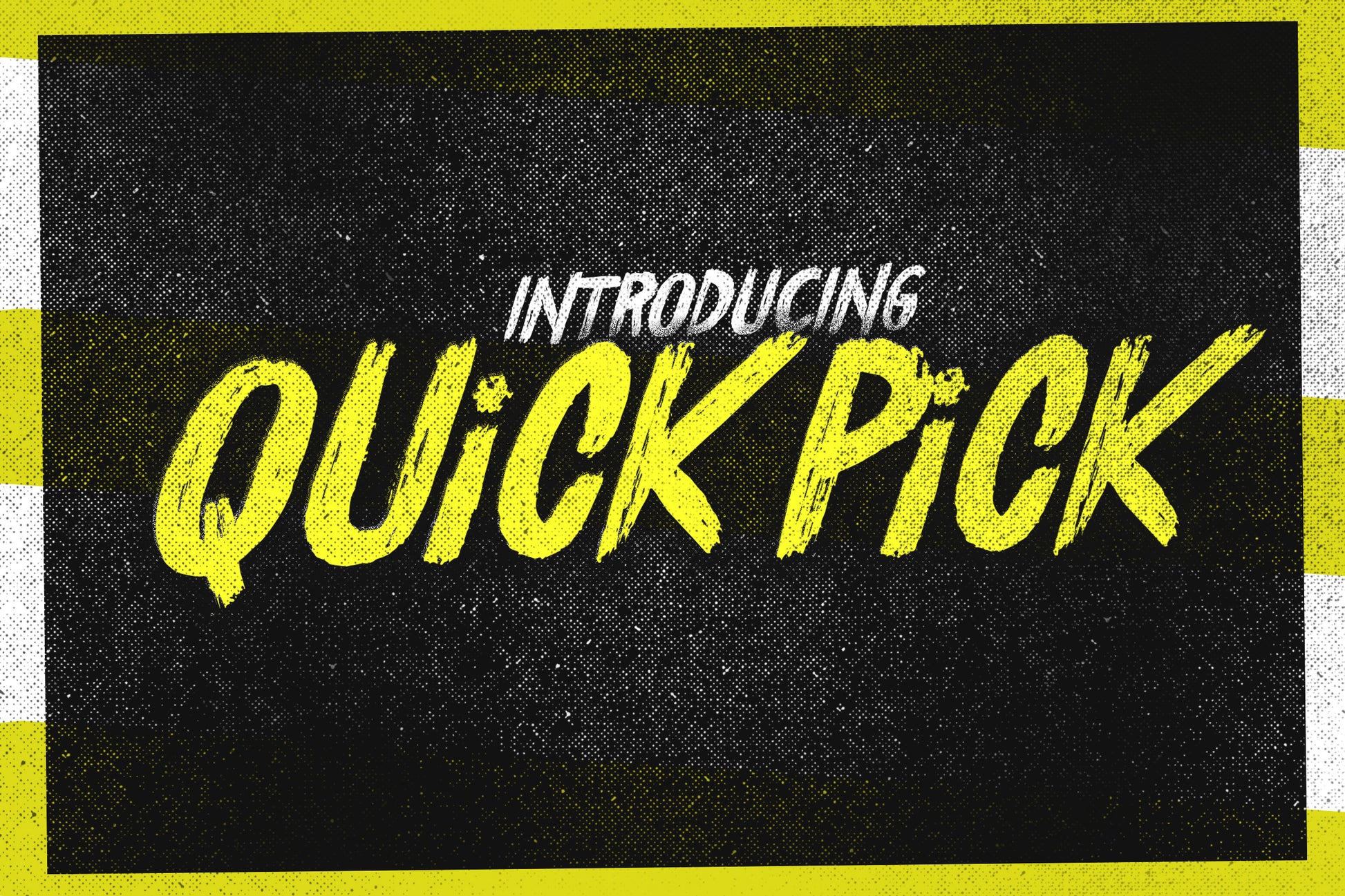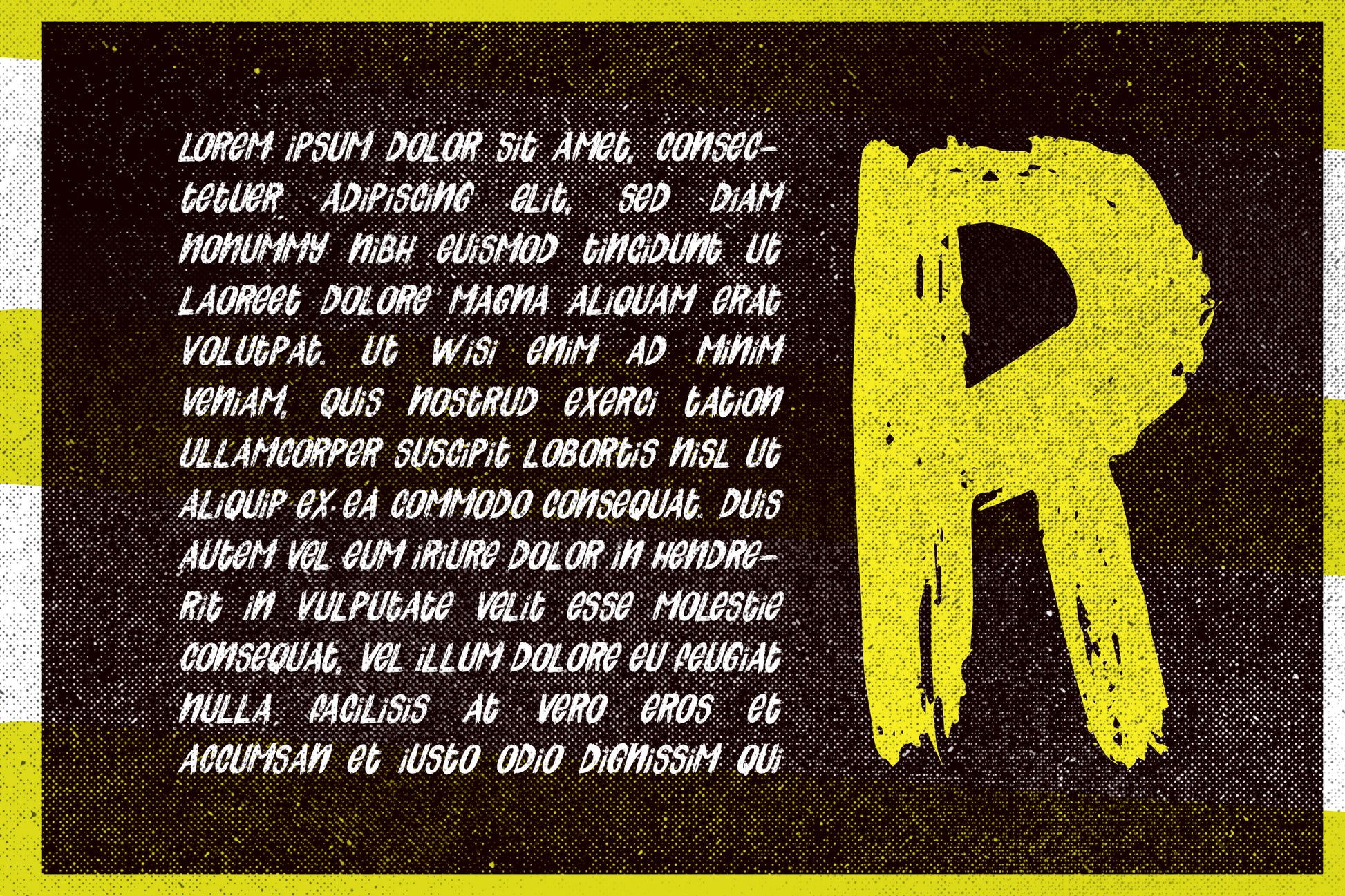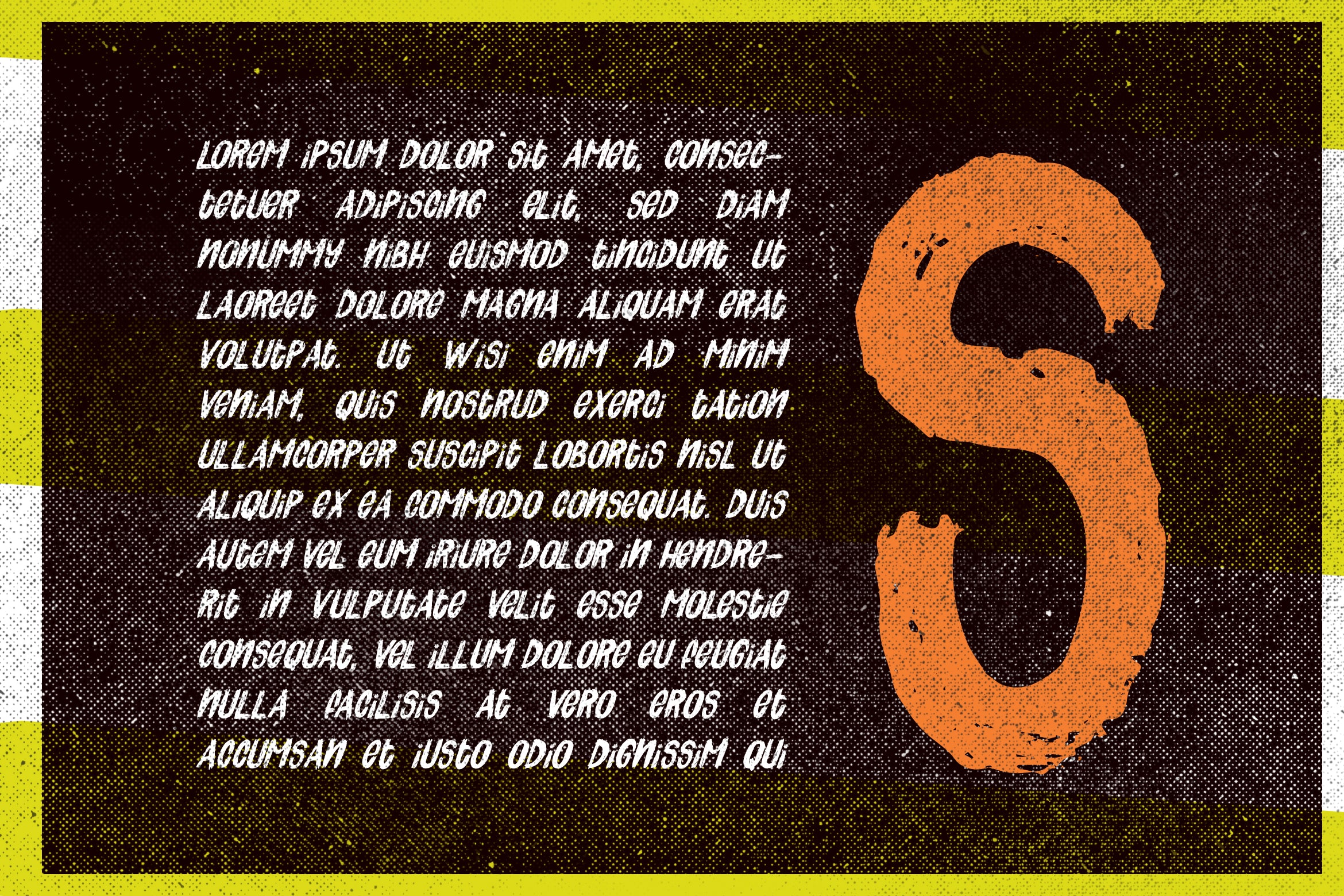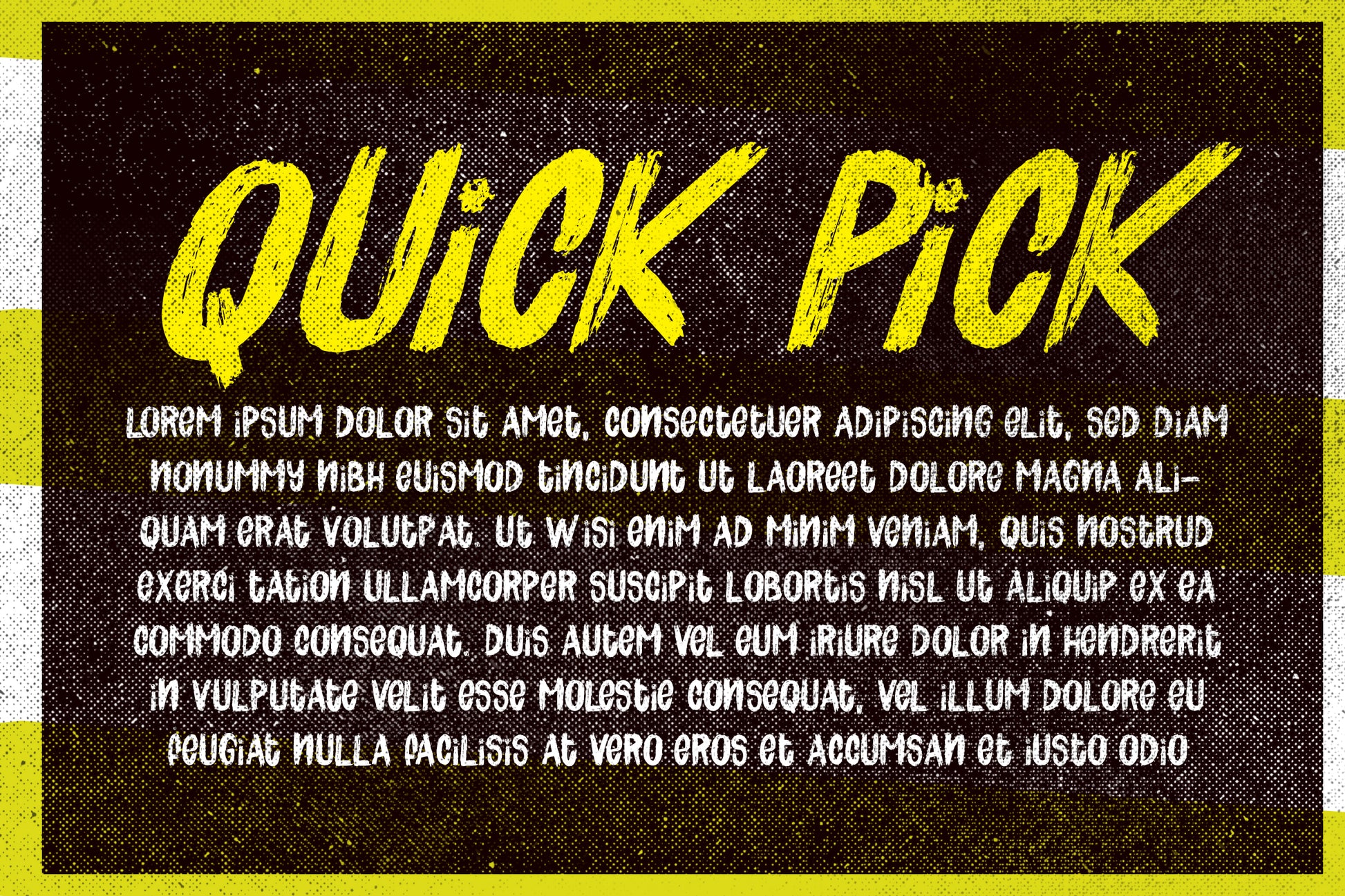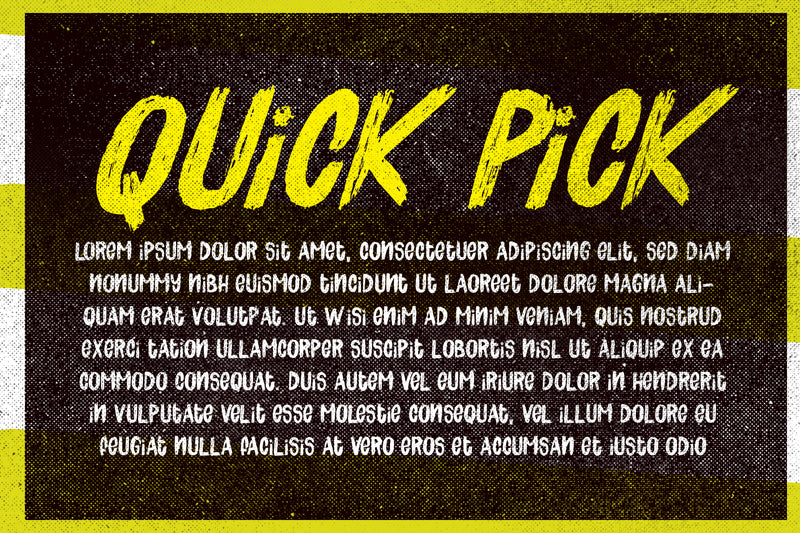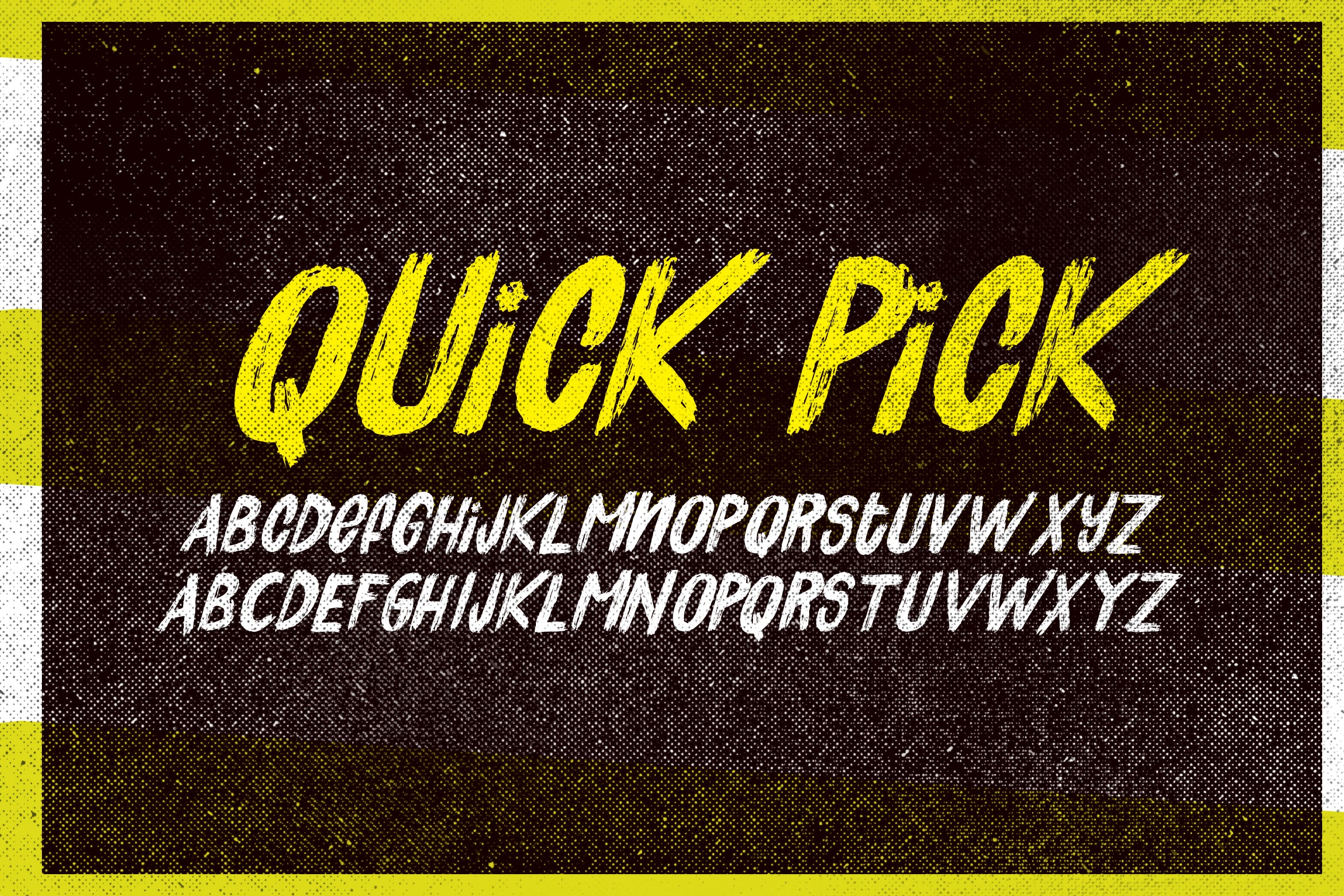
Selección rápida de fuentes
QUICK PICK es una fuente de pincel que incluye todos los glifos estadounidenses y está disponible en versiones regular e inclinada. Ideal para mensajes contundentes. Diseñada con un marcador redondo que le añade movimientos realistas. Ideal para logotipos, etiquetas de nombre, citas manuscritas, empaques de productos, artículos promocionales, redes sociales y tarjetas de felicitación. También es ideal para diseñar camisetas y otras prendas de vestir.
SELECCIÓN RÁPIDA : Fuente con pinceladas manuales que incluye todas las letras mayúsculas, un conjunto completo de la A a la Z y compatibilidad con glifos de EE. UU. Combina mayúsculas y minúsculas para crear estilos de texto interesantes.
QUICK PICK L - Fuente pincelada a mano con inclinación de 17° que incluye todas las letras mayúsculas y un conjunto completo de la A a la Z.